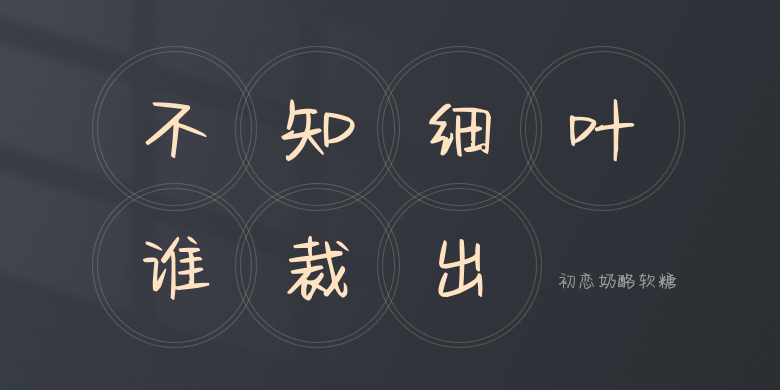
初恋奶酪软糖
初恋奶酪软糖,这款字体结构工整、笔画清晰,兼顾美观与易读性,适用于标题、正文、海报、包装、LOGO 等多种场景。字形优雅稳定,风格百搭耐看,适配日常排版与创意设计,让文字呈现更舒适、更具质感。初恋奶酪软糖一笔一画,皆是细节,以均衡的比例、流畅的线条打造舒适视觉体验,字形端正大气,风格简约现代。无论是商业设计、品牌宣传还是日常排版,都能轻松驾驭,让文字更有格调与力量。初恋奶酪软糖字体下载。